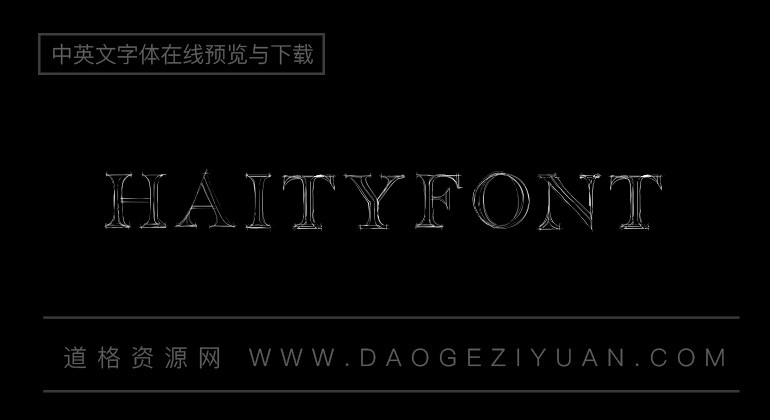
Haityfont 是一种免费开源的中文字体,由经过专业设计师精心设计,拥有清新、活泼、简洁的设计风格。Haityfont 字体拥有丰富的字形,可以满足多种使用场景,可以在网页、报纸、手机应用等多种设计中使用,可以更好地表达你的创意。Haityfont 字体支持中文、英文、日文等多种语言,并且拥有多种字重,可以满足不同的应用需求。内容介绍
Haityfont是一款非常不错的手写艺术字体,具有很好的视觉感,适合于文化类的宣传设计、商业类品牌的广告和产品包装设计以及个性化文字排版等较多场景。